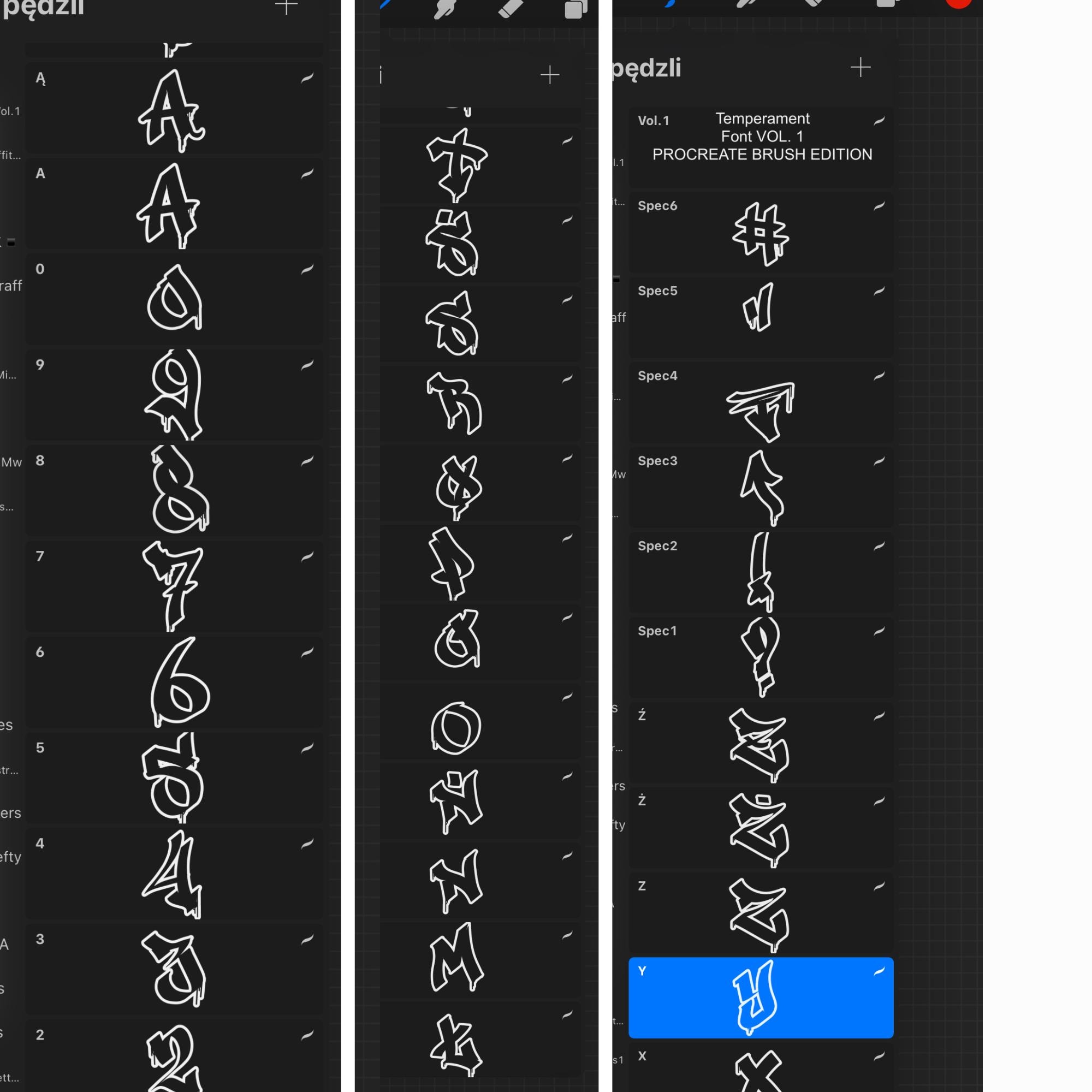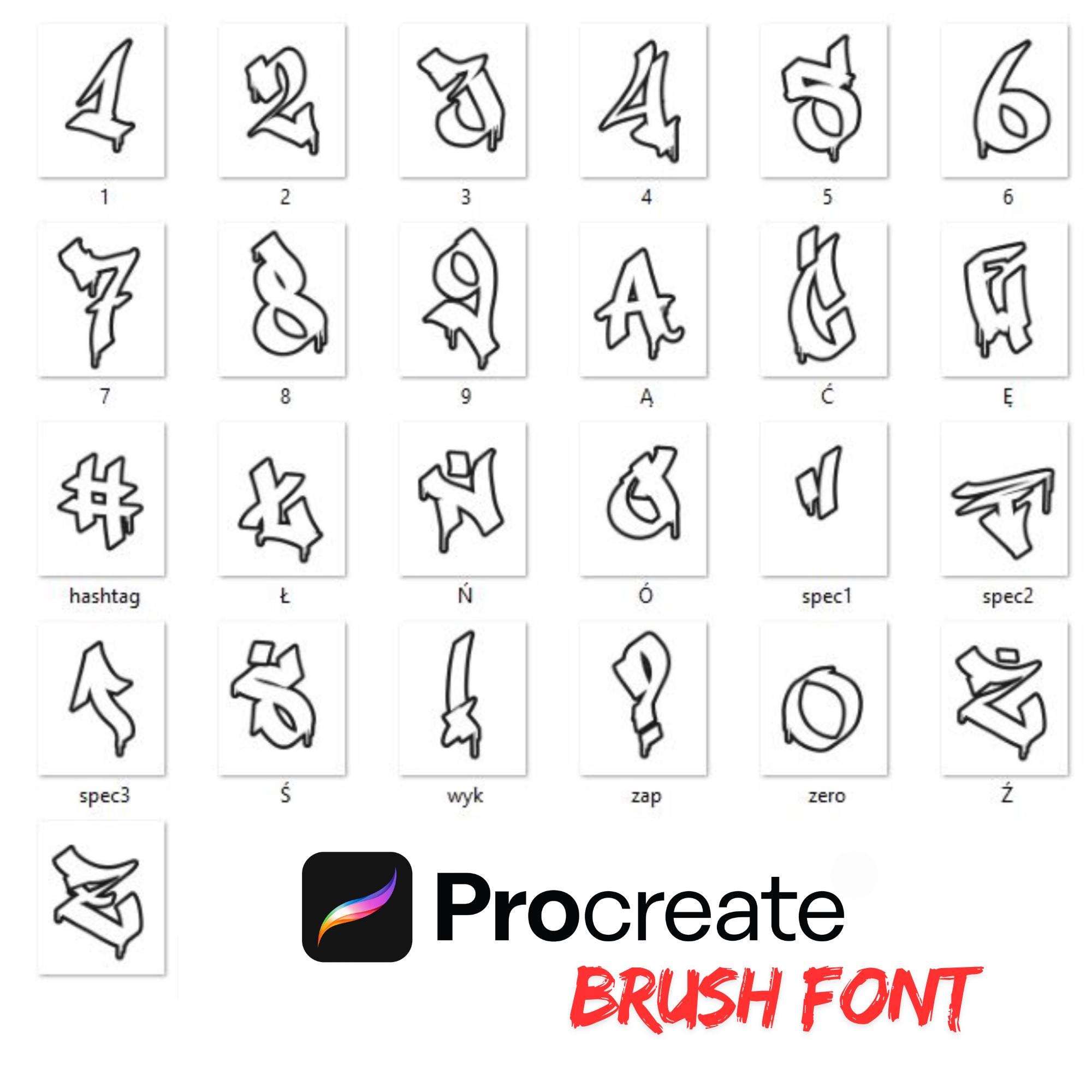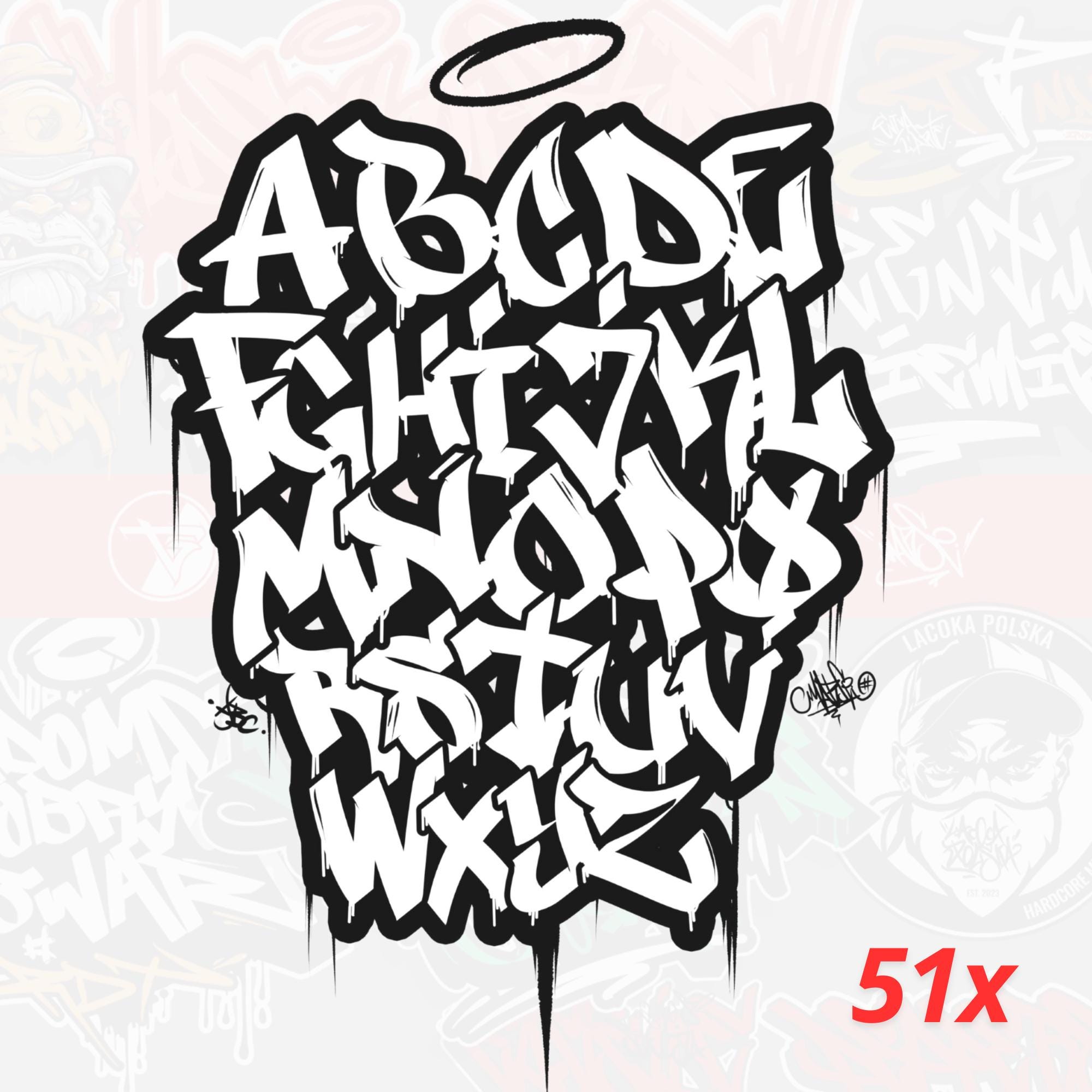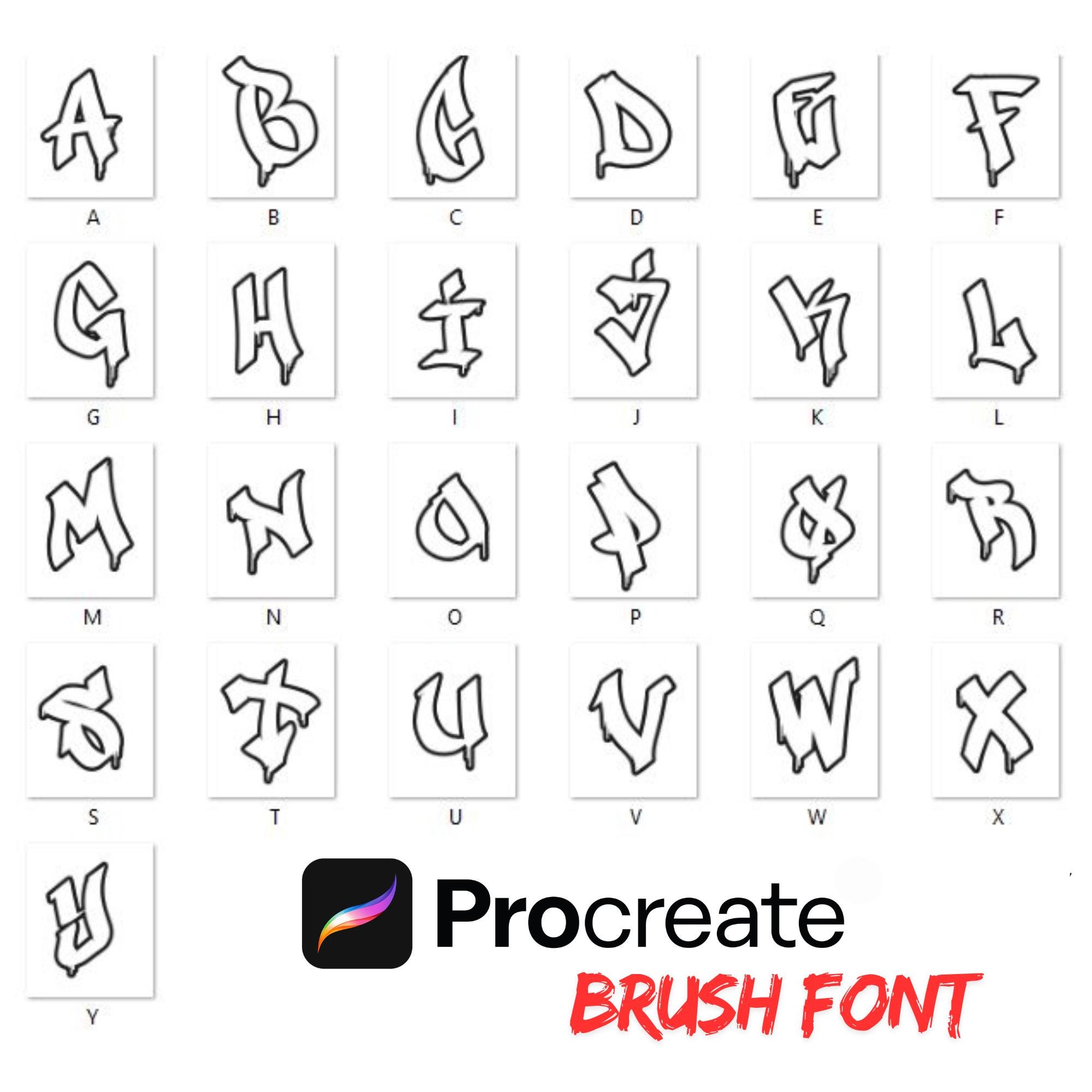
Temperament Font Vol.1 Set de pinceles de graffiti para Procreate – 51 pinceles de lettering urbano
Lleva la energía cruda de la calle a tu iPad con Temperament Font Vol.1: un set de pinceles de graffiti para Procreate con 51 pinceles hechos a mano. Basado en un alfabeto de graffiti original, este conjunto te permite construir lettering urbano y audaz en segundos. Cada letra, número y símbolo es su propio pincel, para componer palabras, tags y layouts sin colocación manual tediosa.
Diseñado para ilustradores, diseñadores y artistas del lettering, estos pinceles capturan el flujo auténtico del tagging clásico, las bubble letters y la tipografía inspirada en el streetwear. Los trazos son suaves, dinámicos y receptivos, ofreciendo resultados nítidos tanto en tags rápidos como en títulos de alto impacto.
- 51 pinceles para Procreate: letras A–Z completas, números 0–9 y símbolos esenciales
- Estética de graffiti auténtica para posters, portadas, logos, publicaciones en redes y más
- Estilo graffiti al instante: inserta letras como pinceles para composiciones rápidas y consistentes
- Control total: cada carácter es independiente; ajusta espaciado, rotación y disposición a tu gusto
- Looks versátiles: de hip‑hop, streetwear y branding urbano a arte digital y mockups de merch
- Calidad de autor: creado a partir de un alfabeto de graffiti original para un verdadero sabor de la calle
- Ahorra tiempo: sin colocación manual ni fuentes torpes; solo estampa, ordena y perfecciona
- Mantén la consistencia: estilo uniforme en letras, números y símbolos
Perfecto para: lettering de graffiti, posters, cover art, branding musical, gráficos para apparel, stickers, visuales para redes sociales y experimentos tipográficos atrevidos.